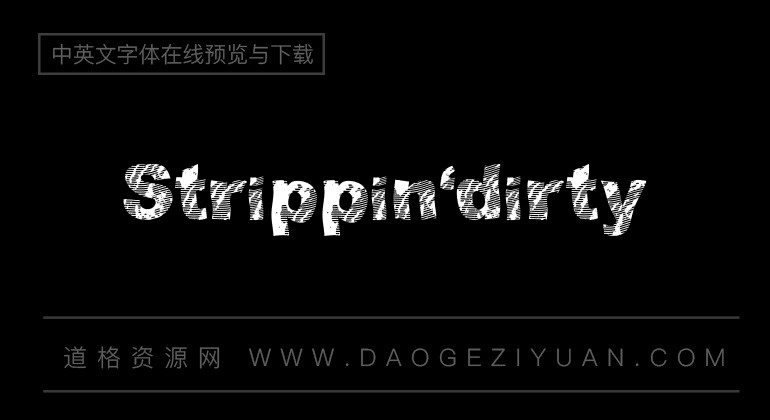
Strippin'dirty
Strippin'dirty 是一款抢眼的粗体字体,具有强烈的视觉冲击力。它具有明显的节奏感,拥有独特的字母形状,充满活力和动感,可以为您的设计带来活力和动感。它具有清晰的线条和明显的节奏感,可以提升您的设计,使其具有更加强烈的视觉冲击力。它适用于标题、标签、海报、海报等,是一款优秀的字体,可以为您的设计带来更多的创意和灵感。
Strippin'dirty是一款非常不错的手写艺术字体,具有很好的视觉感,适合于文化类的宣传设计、商业类品牌的广告和产品包装设计以及个性化文字排版等较多场景。